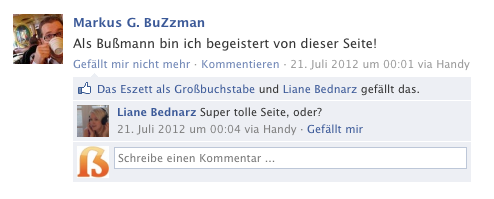
Wenn ich den Duden richtig verstanden habe …
Die Diskussion geht aber grad um die Aussage in dem Schmidt-Buch … ;-) Dass der Duden schon einen Schritt weiter ist, finde ich ja löblich.
Während HÖFER und HOEFER problemlos in einer Datenbank eintragbar oder in einem Pass schreibbar sind, wird WEISS nie zweifelsfrei in gemischte Schreibung wandelbar sein. Nichts anderes meint die Autorin. Und das ist auch keine Geschmacksfrage.
Aber nur in einem kleinen Dorf namens D. In Ländern, deren Tastaturen keine Umlaute kennen, wird auch dein HOEFER nicht zu Höfer, sondern zu Hoefer. Herr HOECKER würde sich bedanken, Höcker geschrieben zu werden … Aber das haben wir ja schon alles zigmal hin- und hergekaut. :-)
Die Diskussion geht aber grad um die Aussage in dem Schmidt-Buch … ;-) Dass der Duden schon einen Schritt weiter ist, finde ich ja löblich.
Ja, verstehe aber nicht, worauf Du Dich dann mit »einzig richtigen versalen Schreibweise« beziehst.  ;-)
Übrigens ist der Genetiv im Schmidt-Buch nicht falsch, sondern nur selten:
Buch|sta|be , der; Gen. -ns, selten -n, Plur. -n
Und schreibt sich der genannte Herr nicht Hoëcker?
Der seltene Genitiv wird üblicherweise nicht in Gebrauchstexten verwendet.
Der Herr Hoecker wurde als Hoecker geboren, sein "Künstlername" ist Hoëcker, damit man ihn nicht Höcker ausspricht.
Aha, wieder was gelernt. Aber Hella von Sinnen nennt ihn doch oft Höckerchen.
Was den Genitiv angeht: Mich hat er nicht gestört. Ich hätte ihn auch so gebildet. Deine Version musste ich erst nachschlagen. Sie war mir nicht geläufig.
Ähem, ich schreibe mal wieder was zum Versal-Eszett, ok?  ;-)
Braucht Deutschland ein Versal-Eszett?
In einer (noch laufenden) Umfrage bei Typolution sagen (bis jetzt) 75% der Befragten »ja«.
Das war zu erwarten … frage ich vom ß Betroffene, ob Deutschland ein Versal-Eszett braucht, werden mindestens 75 % mit nein antworten. :-)
frage ich vom ß Betroffene, ob Deutschland ein Versal-Eszett braucht, werden mindestens 75 % mit nein antworten. :-)
Oho, das bestreite ich vehement! Worauf gründest du diese Aussage? Auf das Ergebnis der Frage in Deinem Familienkreis?
Es ist genau umgekehrt. Wer ein Eszett im Familien- oder Ortsnamen hat, kennt das Problem der fehlenden Versalform sein ganzen Leben lang und die Lösung leuchtet daher umso schneller ein. Ich komme aus einer Stadt mit Eszett im Namen und aus einer Region, wo die Dichte der Familien- und Ortsnamen mit ß am höchsten in ganz Deutschland ist. Ich spreche seit Jahren mit Menschen über dieses Thema – online und offline. Die »Betroffenen« stimmen natürlich am ehesten für diese Lösung – ist es doch die einzige, die den Namen nicht verfälscht. Zögerlich oder ablehnend zeigen sich verständlicherweise gerade die, denen das Thema schlicht im Alltag bzw. der Arbeitswelt einfach noch nicht begegnet ist. Warum sollte man sich auch für Lösungen stark machen, wenn man die Probleme nicht kennt oder sie einen nicht tangieren.
Ich kann mich (neben Dir) nur an einzige Person mit Eszett im Namen erinnern, die sich strikt dagegen ausgesprochen hat. Und das war jemand aus dem Typografie-Bereich, wo sich bei so vielen die vermeintlichen Ligatur-Herkunft vor die eigentliche Funktion des Buchstabens schiebt und man sich dann so eine verquere Historisches-Aussehen-überlagert-heutige-Funktion-Logik zusammen bastelt. Was schon sachlich Unsinn ist.
Von den Betroffenen höre ich Mehrheitlich nur Zustimmung. Deine Zahl erscheint mir ganz weit weg von der Realität.
Feedback der Betroffenen auf unserer Facebook-Seite:
Ich hab die Gegenstimmen von Betroffenen mit Eszett im Namen nicht weggelassen. Es gab keine entsprechenden Kommentare.
Ja, das sind aber alles Menschen, die sich mit Typografie beschäftigen. Das ist aber nun mal eine Minderheit. Kathrins Frage "braucht Deutschland ein Versal-Eszett" ist also klar zu beantworten: Nein, Deutschland braucht es nicht. Eine Minderheit in Deutschland, die sich mit Typografie beschäftigt, hätte es gern.
Diese Frage ist aber grundsätzlich so objektiv zu beantworten wie die Frage, ob Versalien im Französischen mit oder ohne Accent geschrieben werden. Der eine sagt ja, der andere nein. Recht haben sie beide.
Ja, das sind aber alles Menschen, die sich mit Typografie beschäftigen.
Nein, eben gerade nicht. Schau dir mal die »Versal-Eszett-Fans« an, die die entsprechende Facebook-Seite hat. Da dürften mittlerweile weit mehr »Eszett-Betroffene« dabei sein, als Typografie-affine (siehe Zitate).
Eine Minderheit in Deutschland, die sich mit Typografie beschäftigt, hätte es gern.
Die Minderheit ist die, die es erschaffen muss. Wer sonst, wenn nicht jene, die sich professionell mit Schrift aneinander setzen, sollen es denn technisch möglich machen und etablieren. Und das passiert ja gerade. Als es vor 150 Jahren noch kein Ö/Ä/Ü in Druckschriften gab, hättest du auch sagen können: das brauchen die Deutschen ja augenscheinlich nicht. Geht ja auch ohne und die Deutschen fordern es scheinbar auch nicht massenhaft explizit ein. Also ist es nur ein Spleen einer Minderheit? Nene, so klappt die Logik nicht.
Ich bin (wie viele andere auch) der Meinung, dass das ẞ eben nicht der Verständlichkeit dient, sondern eine weitere Fehlerquelle aufmacht. Aber das muss eben jeder für sich entscheiden, wenigstens darin sind wir uns ja alle einig :-)